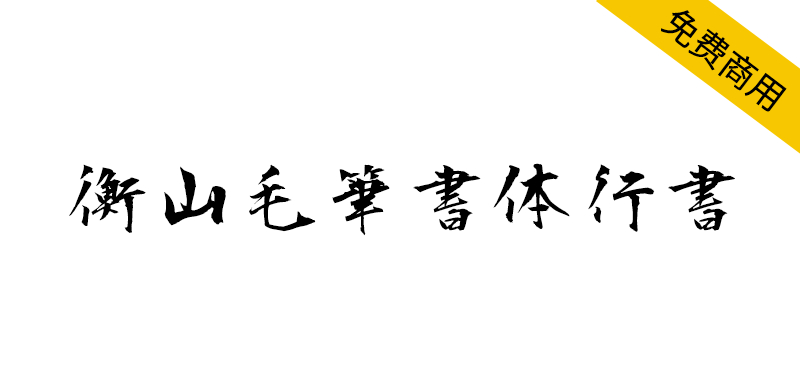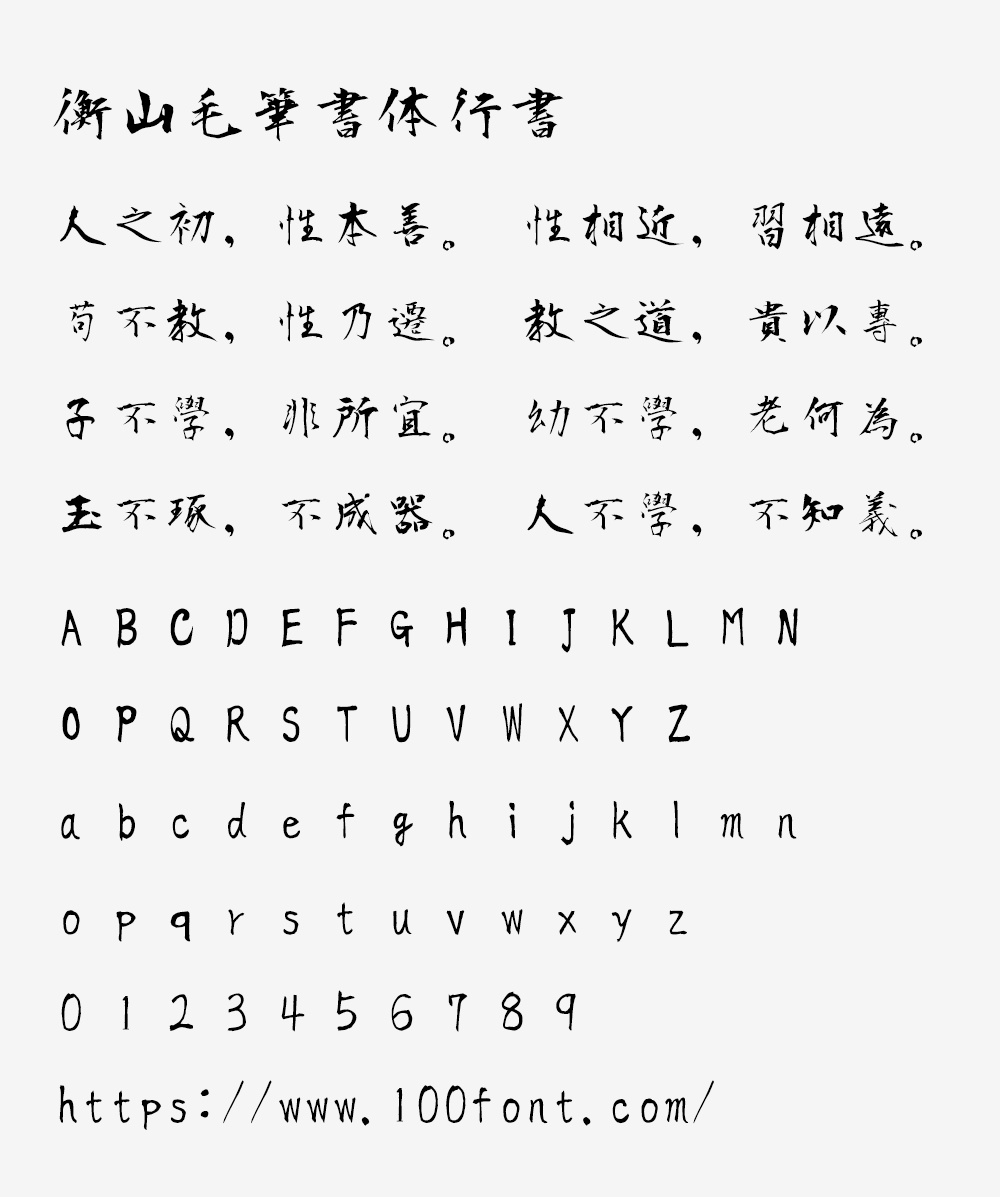
【衡山毛笔字体行书】日本书法家青柳衡山书写的行书字体
衡山毛笔字体行书(衡山毛筆フォント行書)是日本书法家青柳衡山先生书写创作的行书字体,收录了JIS非汉字、JIS第一水平汉字、JIS第二水平汉字,可以免费商用,没有限制,徽标等也可以自由使用,没有任何保证,请自行承担使用风险,在杂志、书籍上使用也是自由的。
書家の青柳衡山先生が揮毫及び作成されたフォントです。JIS非漢字、JIS第一水準漢字、JIS第二水準漢字が収録されています。無料でご利用できます。商用利用可能で制限はありません。ロゴ等へも自由にご利用いただけます。無保証です。お客様の責任でご利用ください。雑誌・書籍への掲載・CD収録も自由です。
【衡山毛笔字体行书】日本书法家青柳衡山书写的行书字体